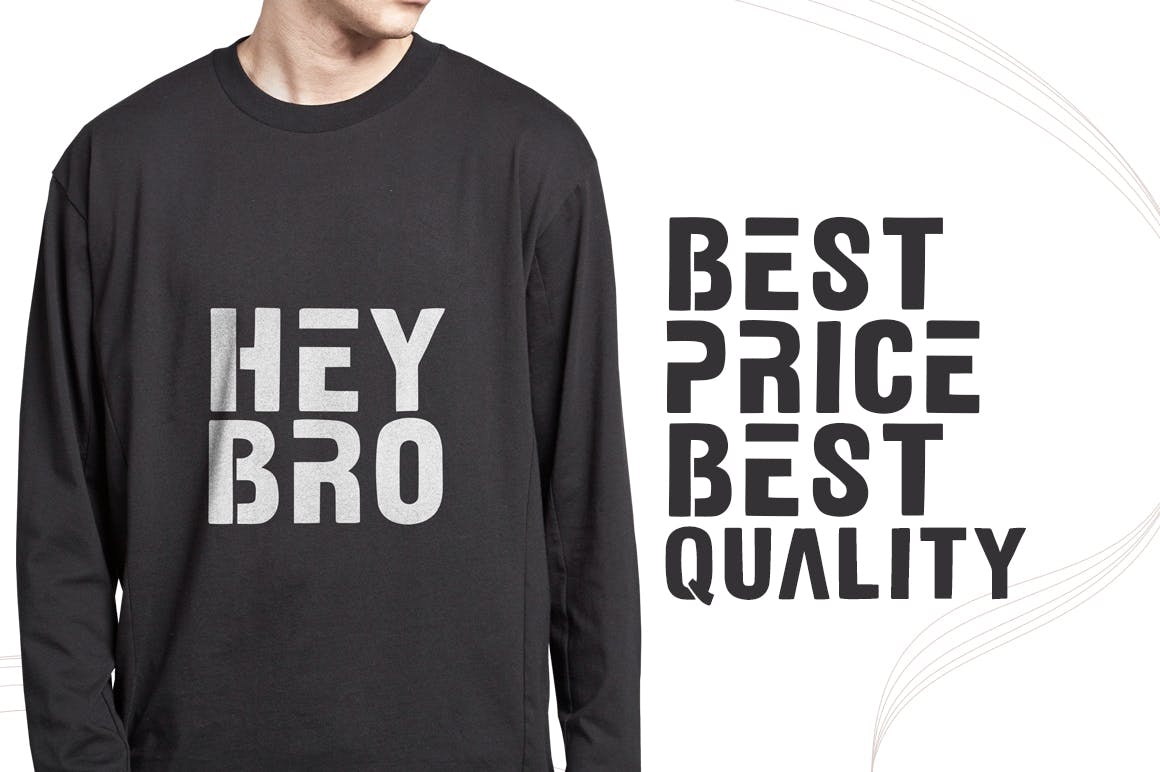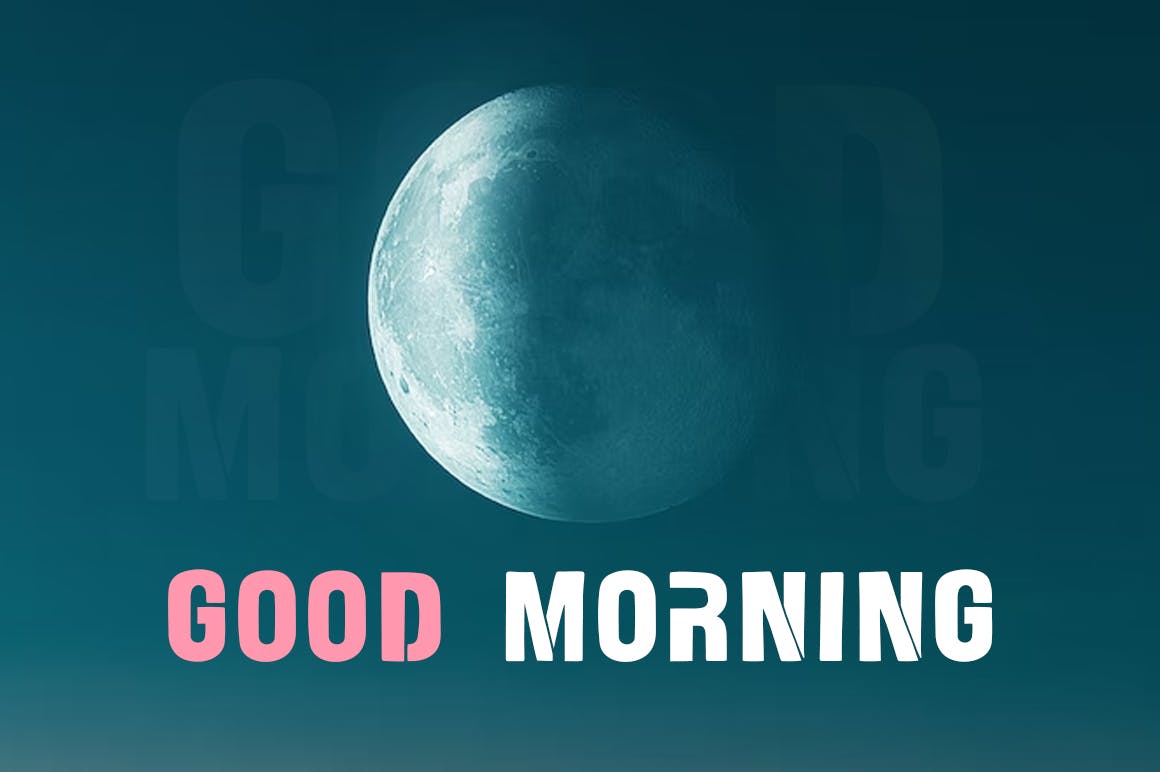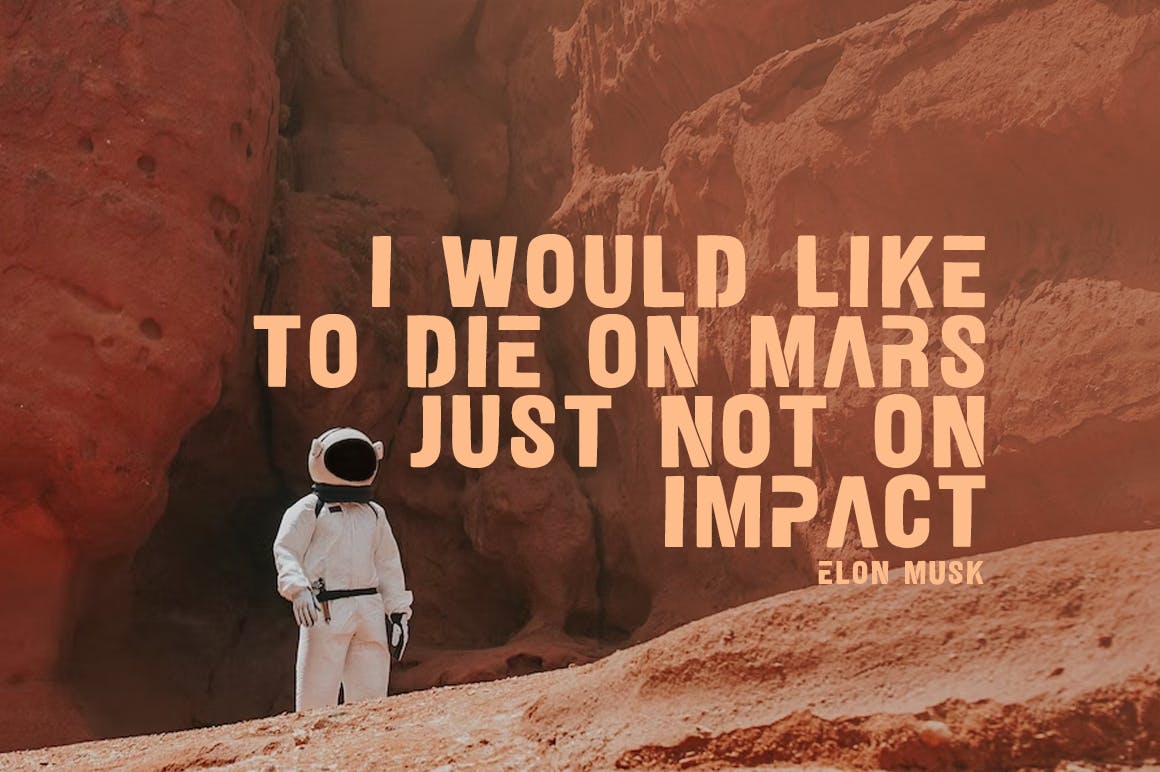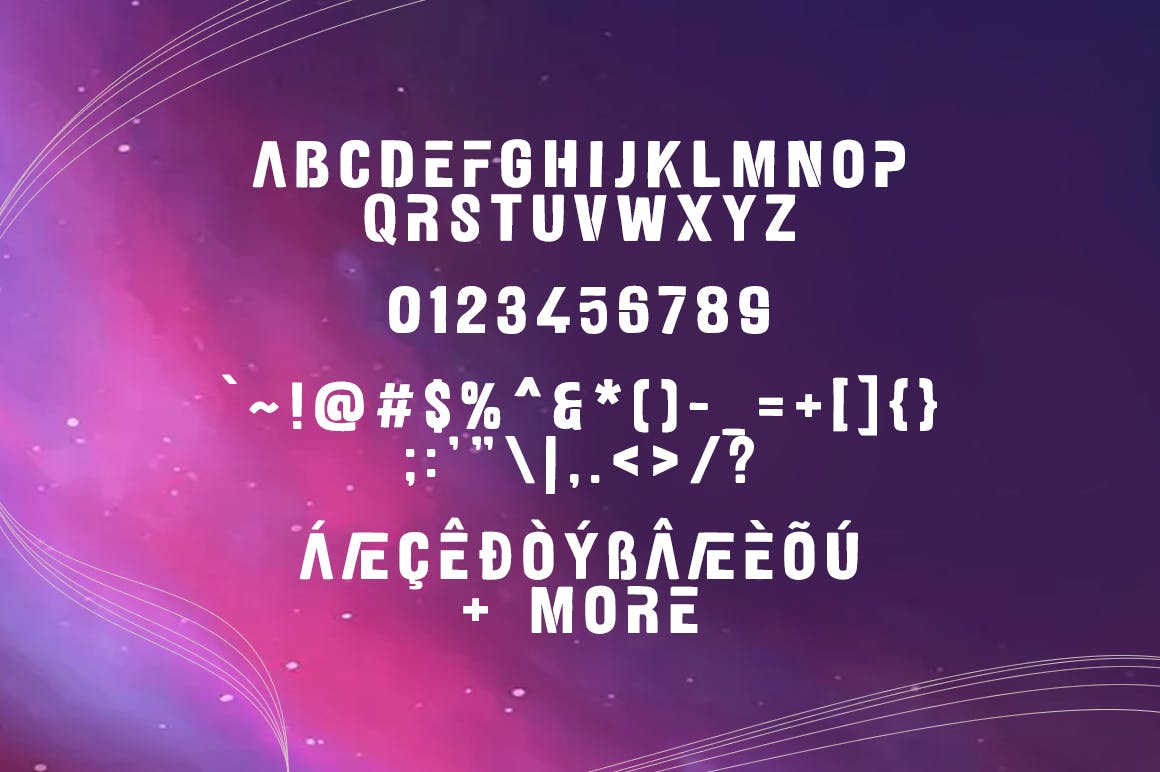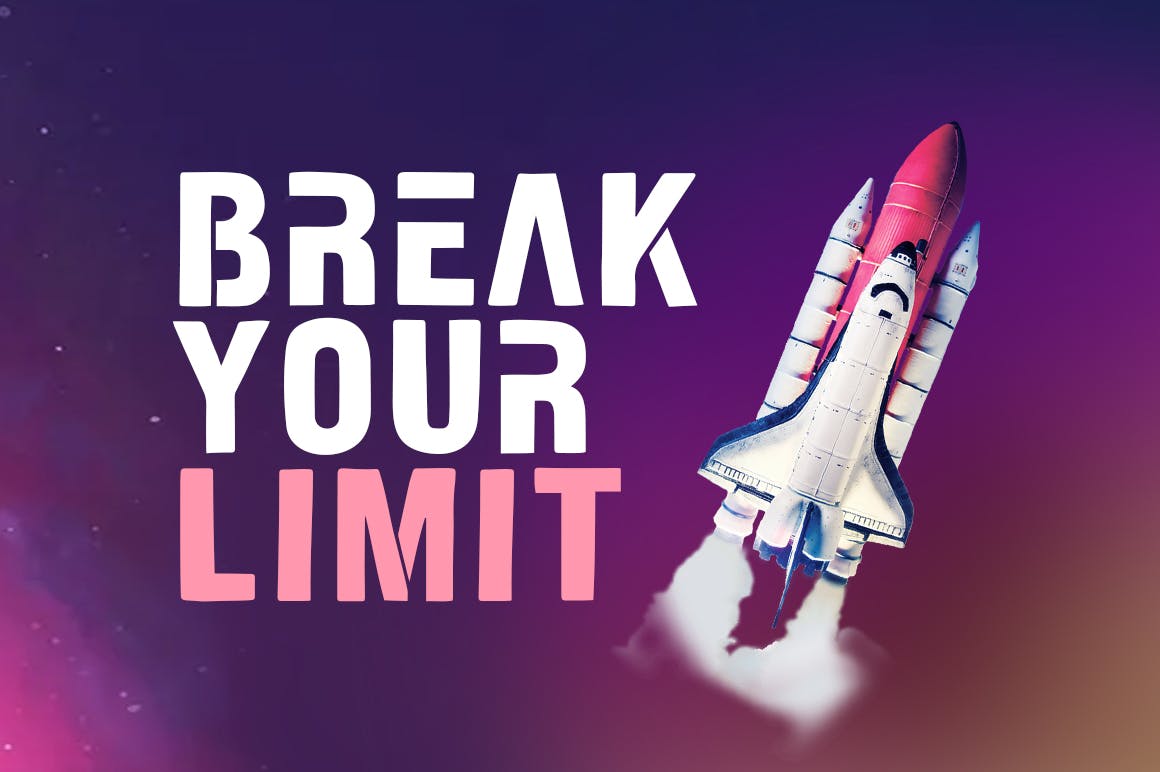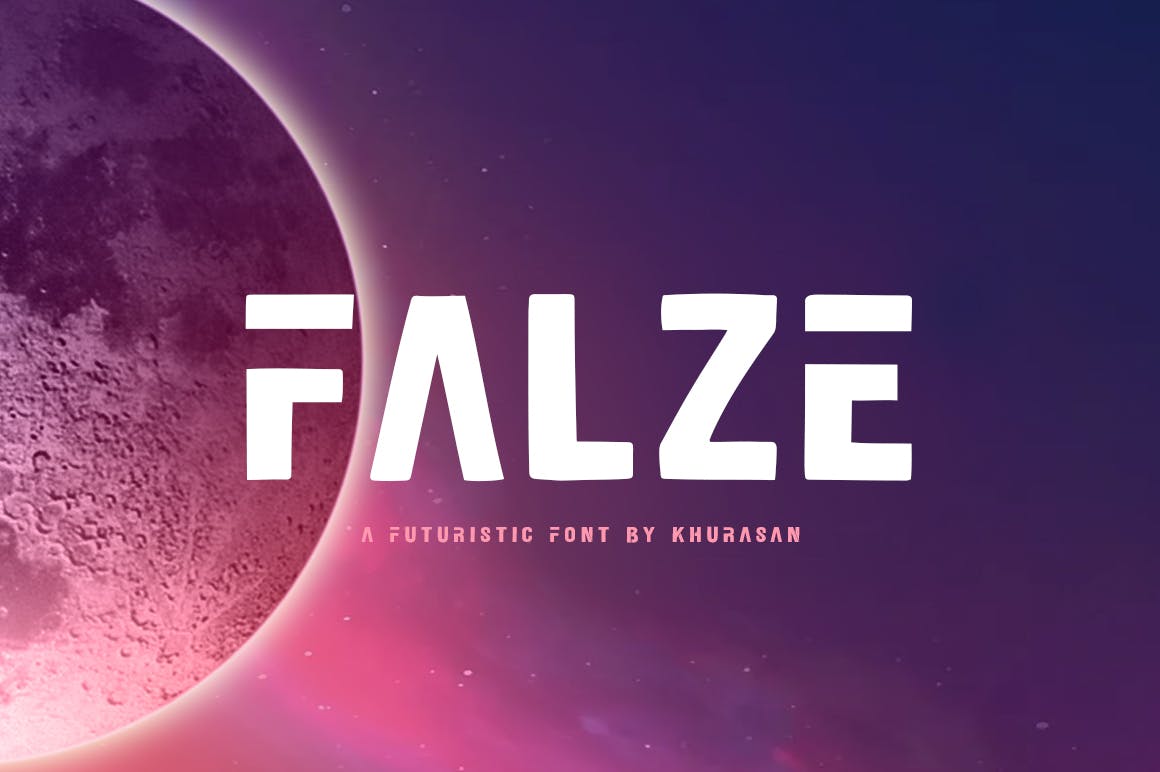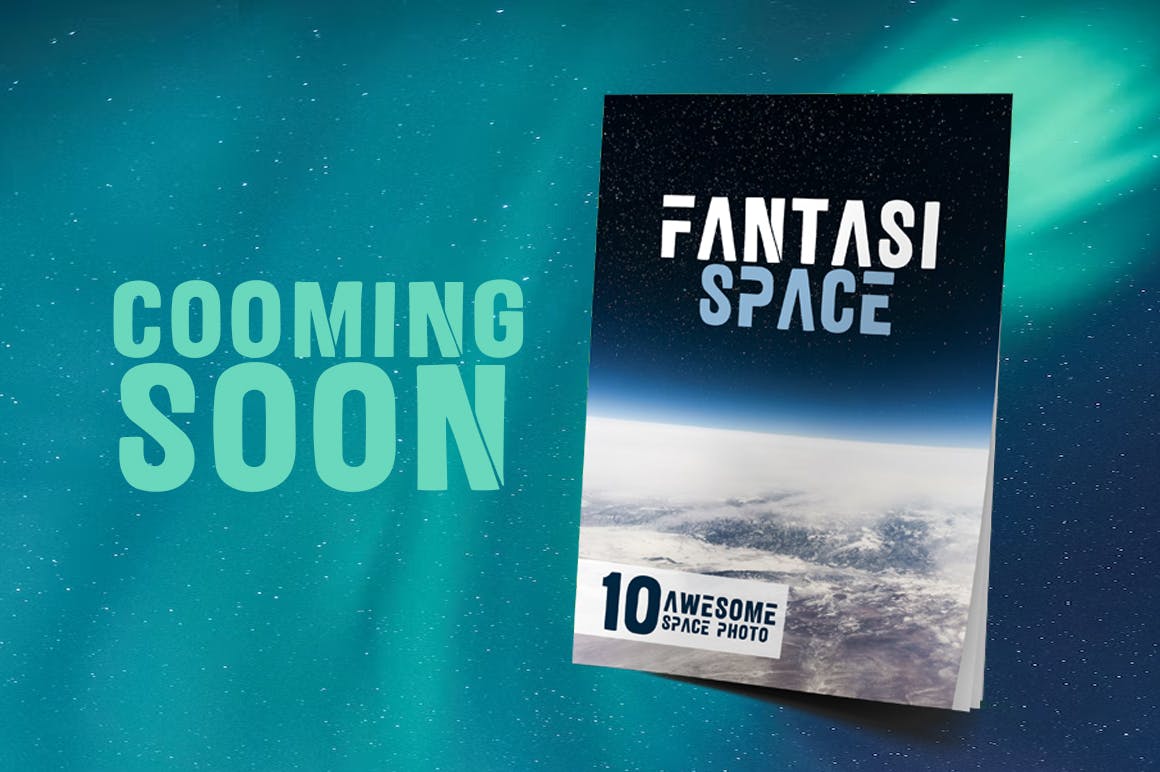
فونت Falze یک فونت منحصر به فرد و آیندهنگر بر پایه sans است که طرحهای شما را مدرنتر میکند. این فونت برای ایجاد لوگوهای مدرن، برندینگ، کارتهای تبریک، پوسترها و هر طراحی که انجام میدهید، مناسب است.